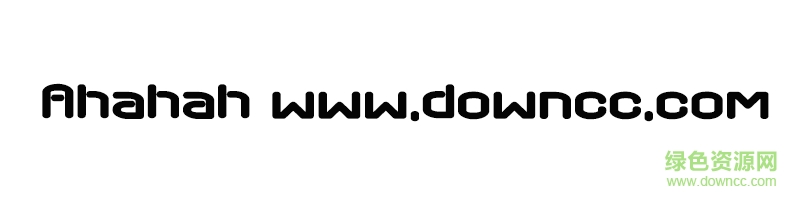
Ahahah字體是一款A(yù)hahah風(fēng)格英文字體軟件,Ahahah風(fēng)格的字體給人非常舒服的感覺,深受廣大年輕人的喜愛,還有更多好看字體盡情期待,歡迎到綠色資源網(wǎng)下載體驗!
Ahahah是一款A(yù)hahah風(fēng)格英文體字,字體效果比較滑稽,喜歡英文字體的朋友可以下載使用看看效果如何。